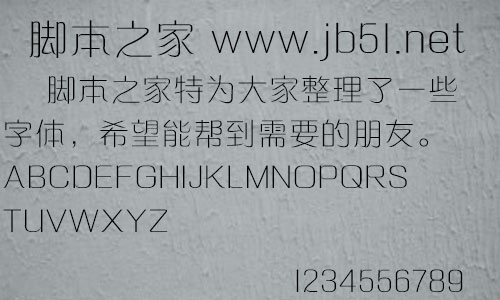
方正細(xì)倩_GBK字體是方正字體庫中的一種字體,其筆畫銜接和轉(zhuǎn)折均為圓弧形,筆形和字形的設(shè)計(jì)注重對稱均衡。適合應(yīng)用于藝術(shù)設(shè)計(jì)、平面宣傳設(shè)計(jì)、網(wǎng)頁設(shè)計(jì),書法字帖等領(lǐng)域。喜歡的朋友們可以前下載使用。